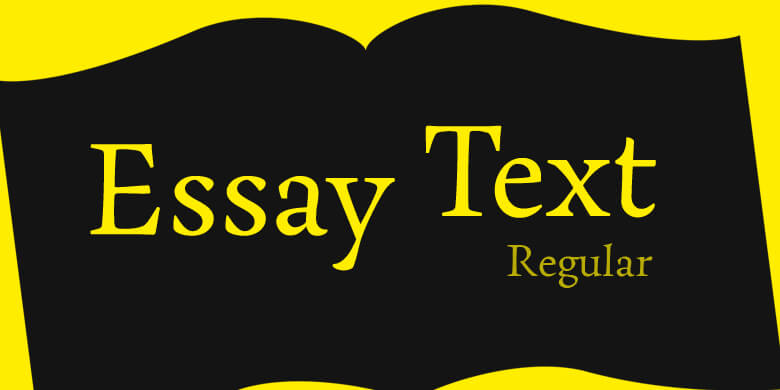
Essay
Essay,这款字体结构工整、笔画清晰,兼顾美观与易读性,适用于标题、正文、海报、包装、LOGO 等多种场景。字形优雅稳定,风格百搭耐看,适配日常排版与创意设计,让文字呈现更舒适、更具质感。Essay一笔一画,皆是细节,以均衡的比例、流畅的线条打造舒适视觉体验,字形端正大气,风格简约现代。无论是商业设计、品牌宣传还是日常排版,都能轻松驾驭,让文字更有格调与力量。Essay字体下载。
埃尔默·史蒂芬设计的一款优雅的衬线体,拥有广泛的文字排印功能